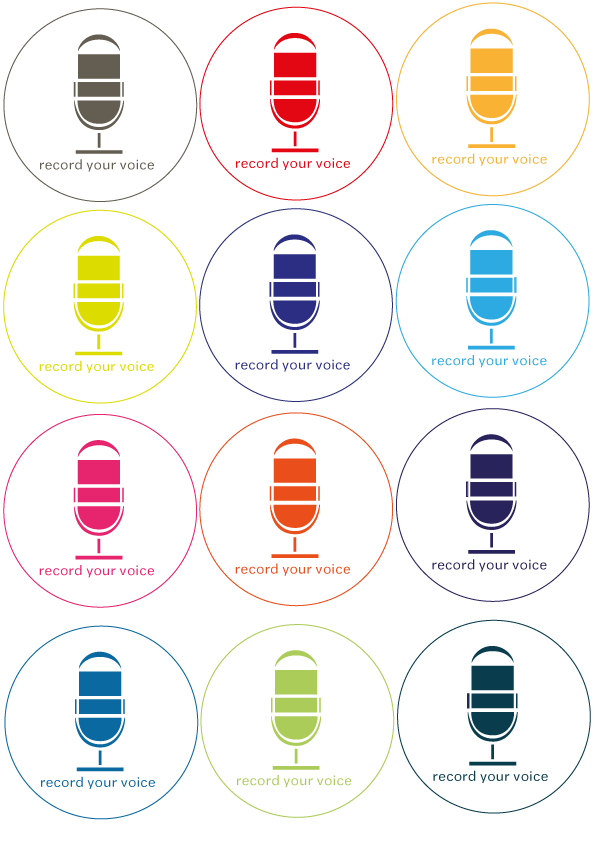
stylisch, trendige Schrift für Aufnahmestudio gesucht. Zielgruppe: Jugendliche
*staun* Das ist ja Unicode! Danke für den Hinweis:
was haltet ihr eigentlich wenn ich das ganze nur stimmdesign nenne?
Record your voice bzw. alles andere kann ich ja in den normalen text übernehmen...
anbei noch eine neue version, noch nicht ausgereift was sagt ihr grundsätzlich zur idee?
Schriftmäßig habe ich noch nicht viel gemacht... lg
Grundsätzlich: Ja, warum nicht :) Aber: Das Mikro ist so viel zu groß: überleg wie groß Du das Logo drucken müsstest (auf ner Geschäftskarte oder was ähnlich kleinem) damit die Schrift noch zu sehen ist ... ;)
Diese Art von Mikros gab es auch mit schönen Schildchen (drittelkreisförmig) drauf. Dadrauf standen dann immer die Sendernamen. Mache nun das Mirko kleiner, übertreibe das Schild in der Größe und setze die Schrift da drauf? Das ganze im Holzschnittstil und fertig ist die perfekte Karikatur.
Bei dem neuen Logo von Cafejunge habe ich zuerst hochgezapfte Biere gesehen und dann erst ein Mikrofon erkannt.
So ging's mir auch...
dto.
+1
Wobei der Ansatz, das stilisiert darzustellen, gefällt. Müsste aber ein guter Illustrator ran …
So! hier noch mal in möglicher Vollfarbe.
Das Mikro selber werde ich noch überarbeiten, damit das biermäßige verschwindet.... aber was sagt ihr zu den Farben? Schrift glaube ich muss auch nochmal jungendlicher werden...... Danke
Also ich seh auch eines ;-)
Hallo und Prost,
sagt mal: Bin ich der Einzige der ein Kondensatormikrofon gesehen hat? Muss ich mich jetzt als Außenseiter fühlen?
:roll:
Lass doch mal die Farbspielereien weg und konzentrier dich auf das Motiv an sich. Das Mikro sollte nicht wie ein Bierglas aussehen, und auch nicht wie eine Medikamentenkapsel auf Stelzen.
Die Schrift sollte vor allem gut zu lesen sein, damit die Leute wissen wie du heißt. Bei deinem Entwurf finde ich sie zu klein und zu dünn. Als zweiten Schritt kannst du stilistisch passende Schriften durchtesten.
Ich hab mal schnell was skizziert und der Einfachkeit halber die Myriad Pro Black Condensed genommen:
Das ist jetzt eine eher traditionelle Optik, allerdings könnte sie gut als CD-Aufdruck passen.
Hauptzielgruppe sind Jugendliche.
Na, denn: Sex, Gewalt und Rock’n’roll.
Ich befürchte dass Jugendliche mit dieses gar nicht als Mikrofon erkennen.
Ich könnte mir schon vorstellen, dass Jugendliche das Mikro erkennen, weil die Dinger oft als nostalgische Requisite in Musikvideos auftauchen. Ich frage mich aber, warum das Mikrofon so statisch und mittelachsensymmetrisch dargestellt werden muss. Ich fände eine asymmetrische Darstellung wesentlich spannender und auch eindeutiger, weil gewisse Verwechslungsgefahren wegfallen würden.
:nicken:
Das muss dann aber auch gekonnt sein ...
Oder Du lässt das halt doch mal ordentlich machen ... :-?
Du willst mich wohl ärgern!
Ich bekomm das schon noch so hin das es gut wird.
Und Bier und Jugendliche.... passt eigentlich eh ganz gut...
Du willst mich wohl ärgern!
Näh :) Aber Du wagst Dich da gerade an so ziemlich das schwerste ran, was man als Designer machen kann ...
Und Bier und Jugendliche.... passt eigentlich eh ganz gut...
Auf die Assoziation würde ich es lieber nicht anlegen, aber das ist nur mein persönliches Empfinden.
Näh :) Aber Du wagst Dich da gerade an so ziemlich das schwerste ran, was man als Designer machen kann ...
wieder ne Herausforderung!
Ich lass mir gerne tipps geben, aber das is mein Projekt und das muss auch von mir sein.
Was Minimalist da sagt, ist schlicht und ergreifend ein Erfahrungswert – es gibt kaum etwas Schwierigeres, als das eigenen Corporate Design zu entwickeln. Ich habe renommierte Designagenturen erlebt, die sich dafür entschieden haben, ihr eigenes CD von externen Gestaltern entwickeln zu lassen – aus genau diesem Grund. Und das ist absolut kein schlechter Ansatz – sich einzugestehen, dass die eigene Betriebsblindheit der Entwicklung des eigenen Erscheinungsbildes womöglich im Wege steht. Es geht hier an dieser Stelle nicht darum Dich zu provozieren, warum auch. Aber ein kleiner Hinweis darauf, dass Du Dir da etwas Schwieriges vorgenommen hast und dass auch eine abgeschlossene Gestalterausbildung nicht unbedingt heißen muss, dass man mit jeder (schwierigen) Aufgabe zurecht kommt, muss erlaubt sein – die vielen guten Ratschläge hast Du ja auch schon bekommen. :-)